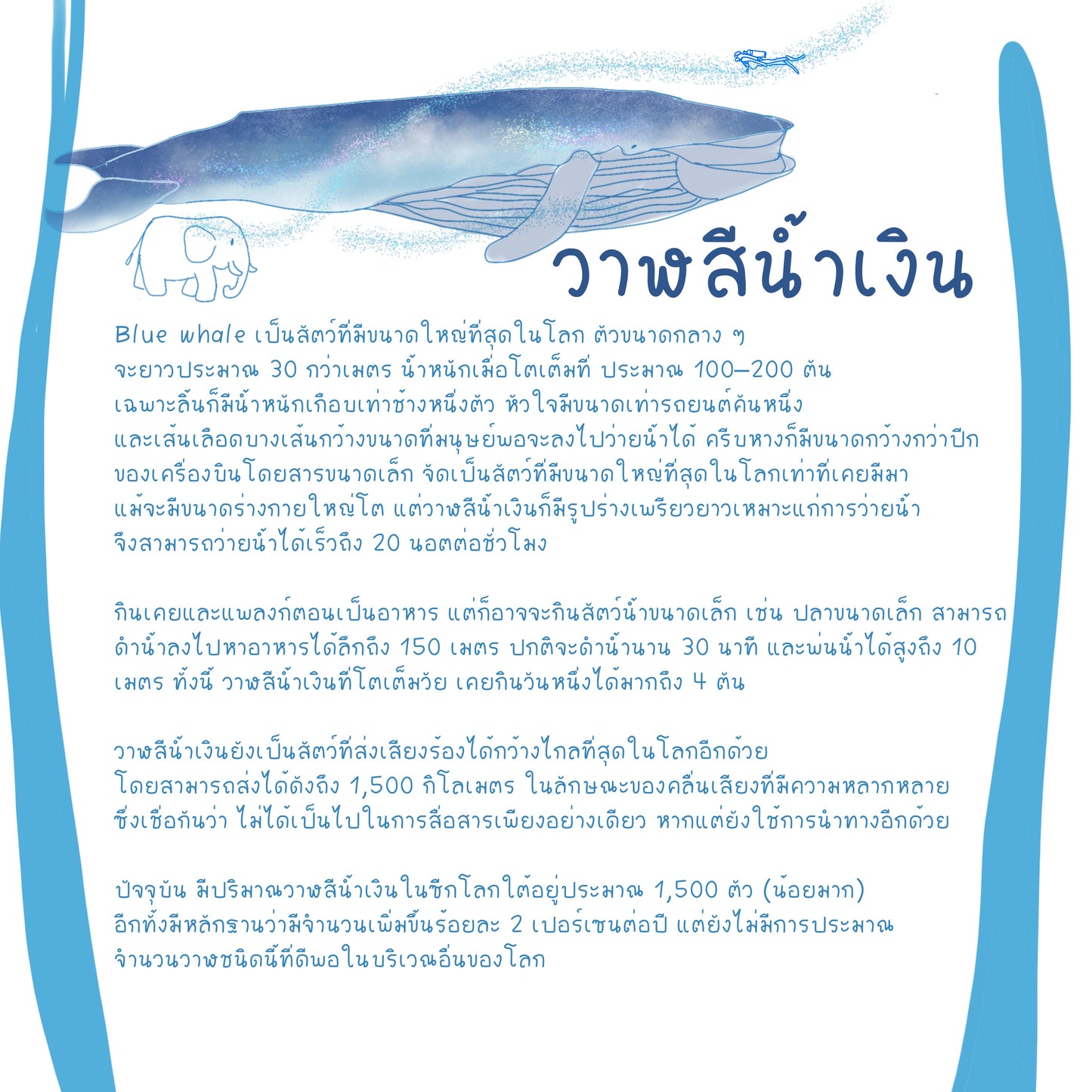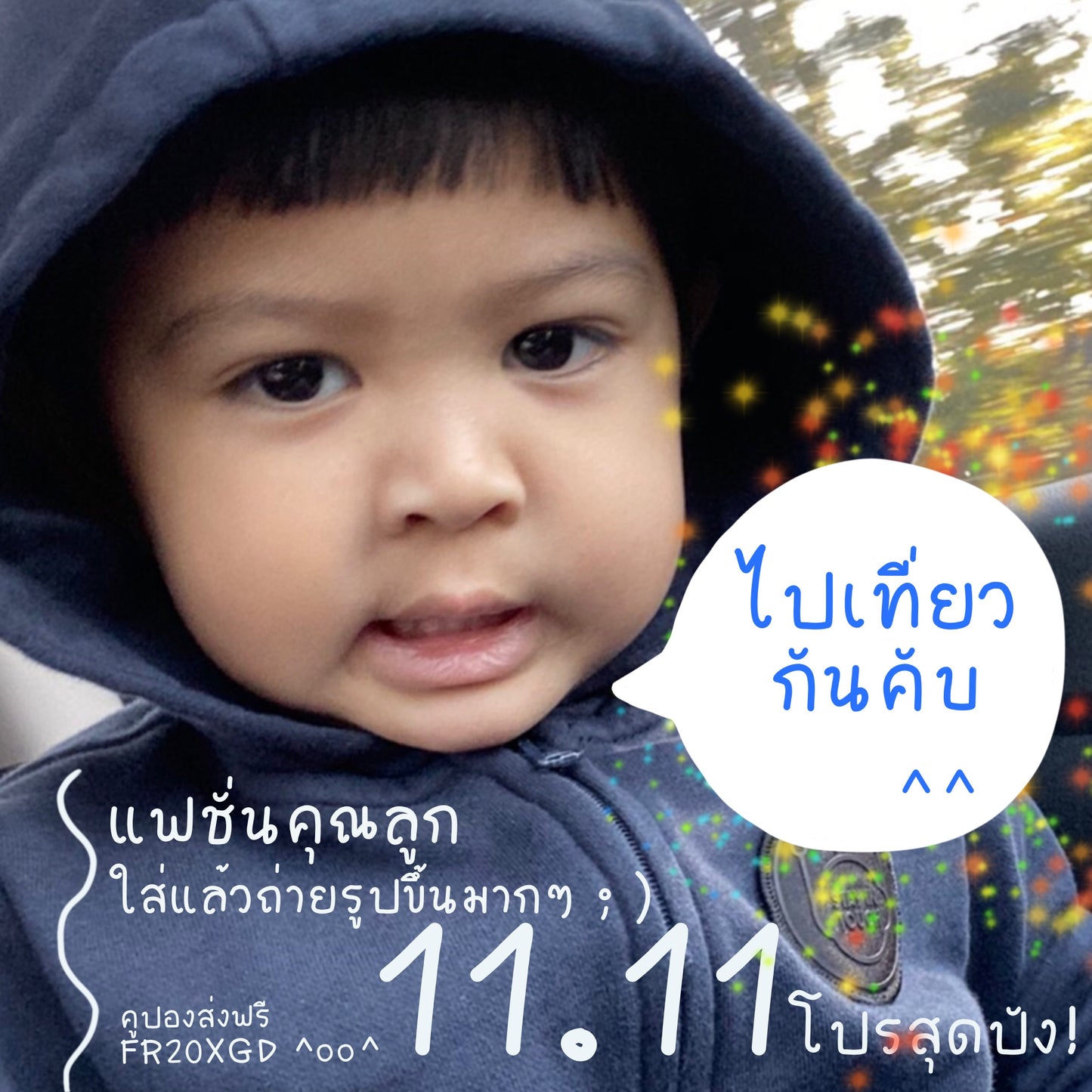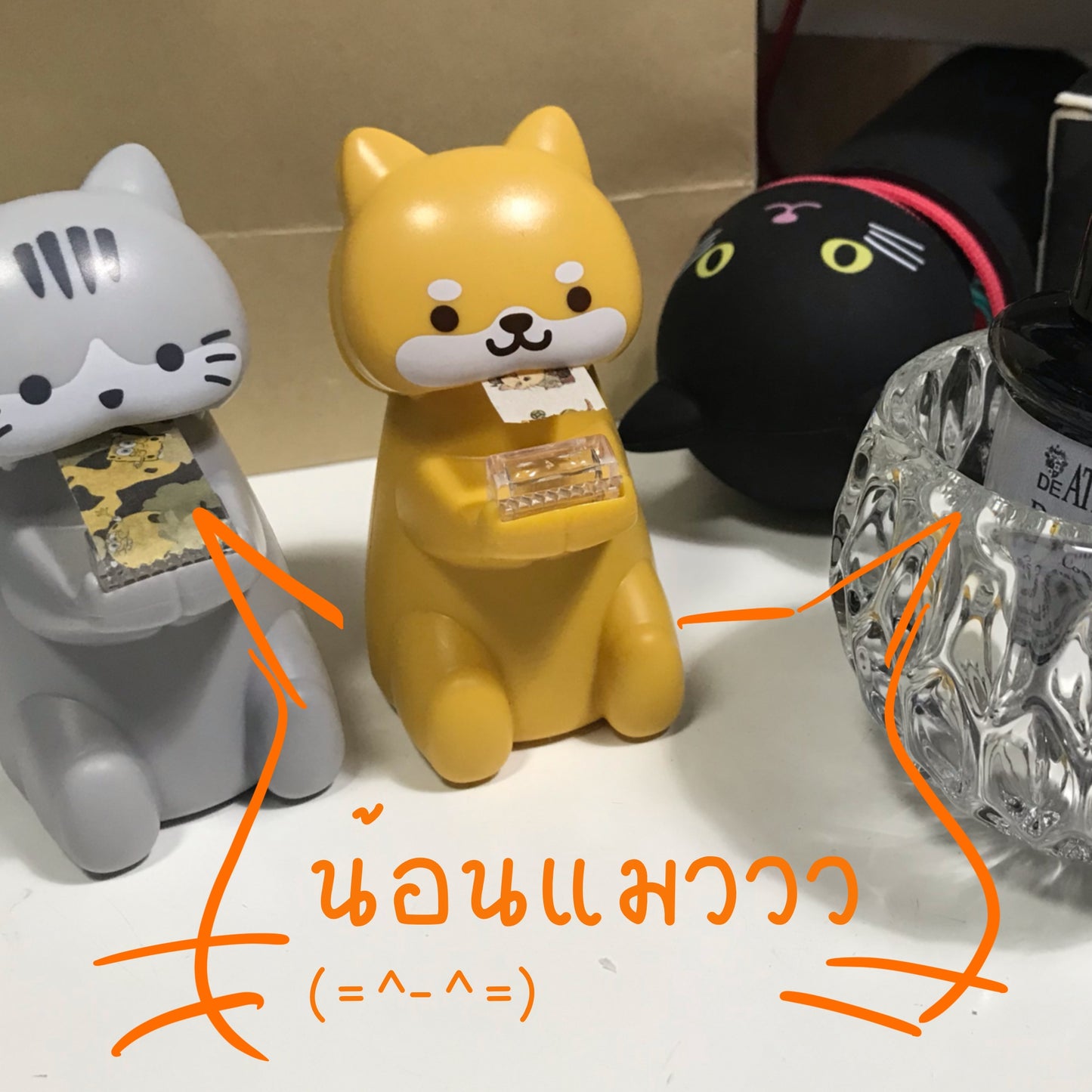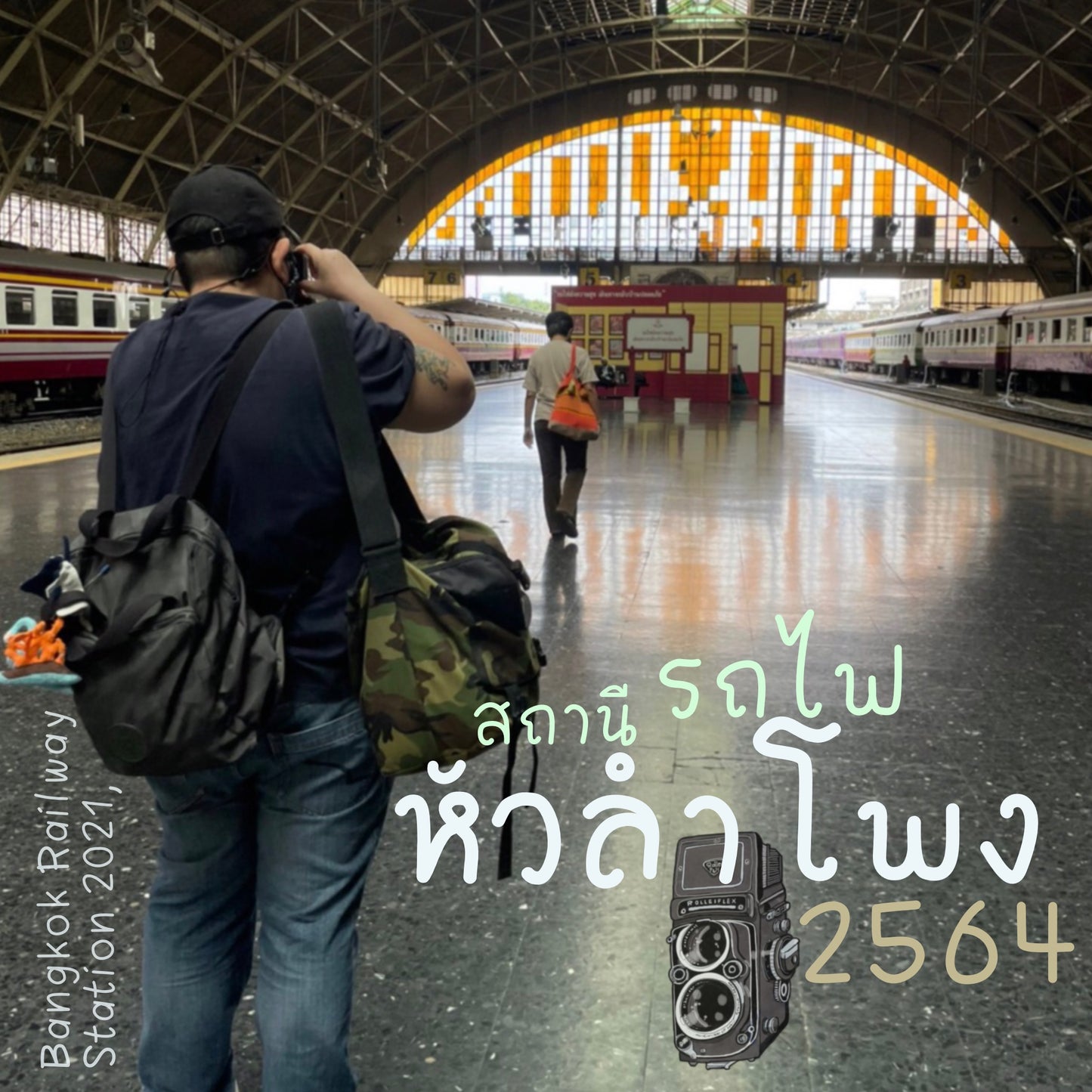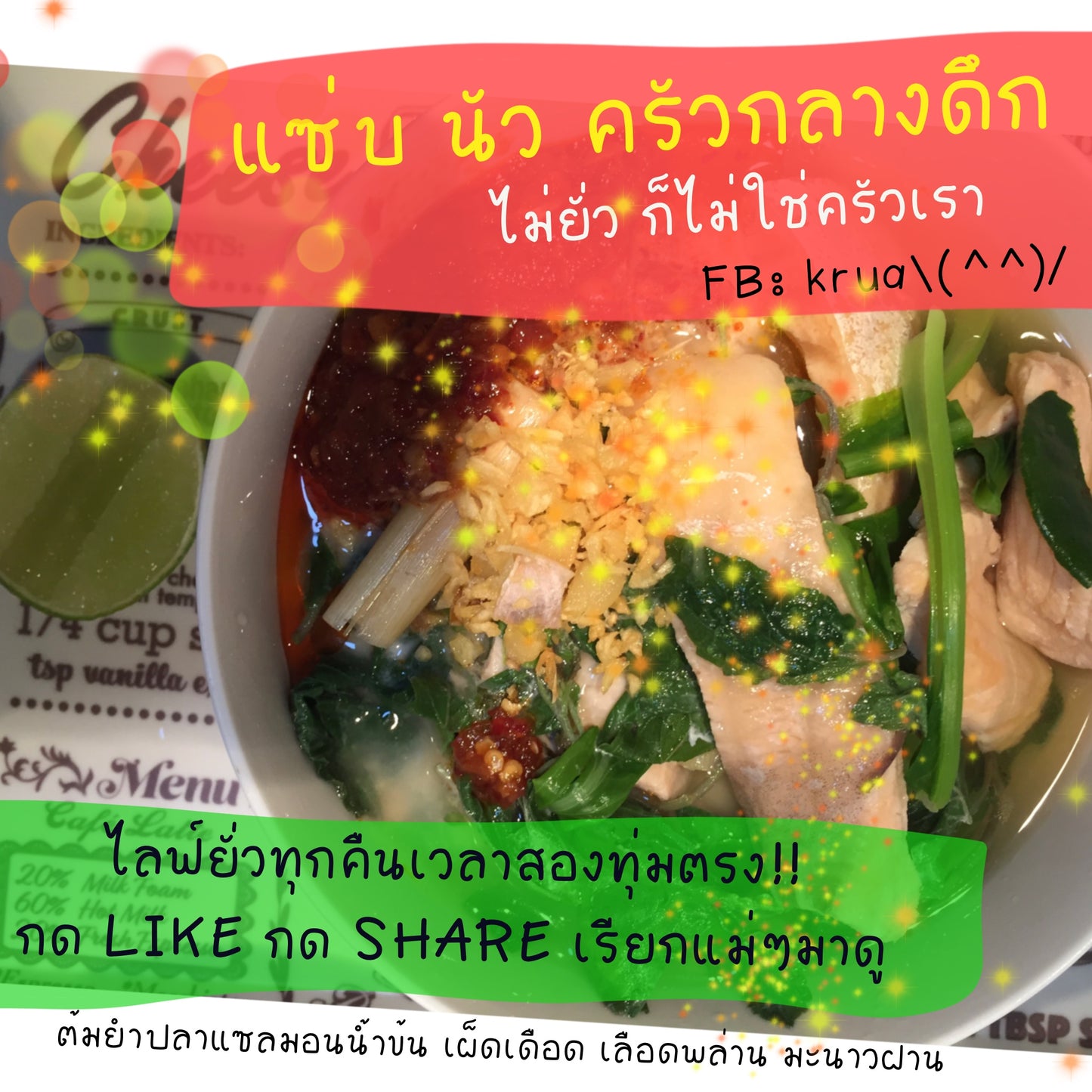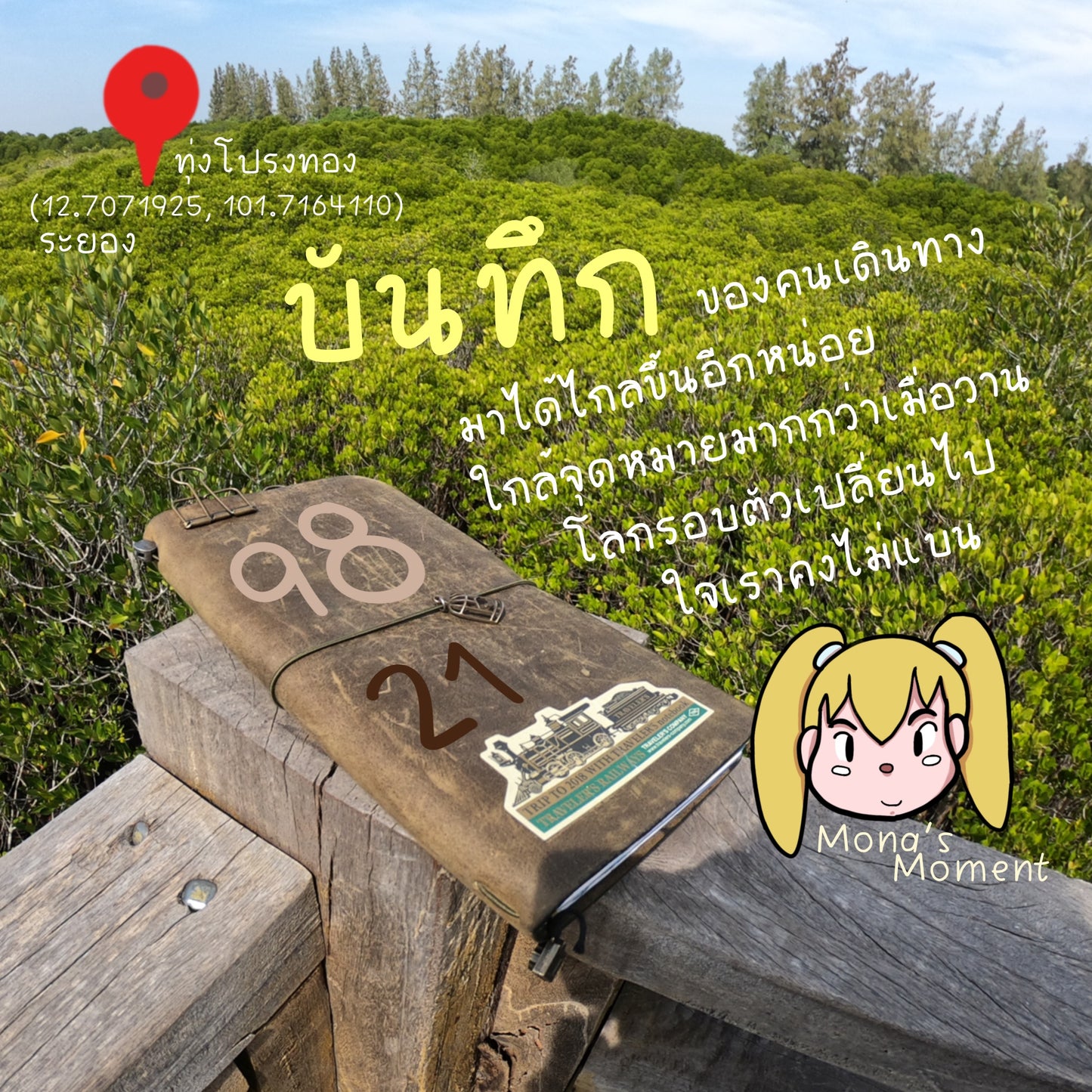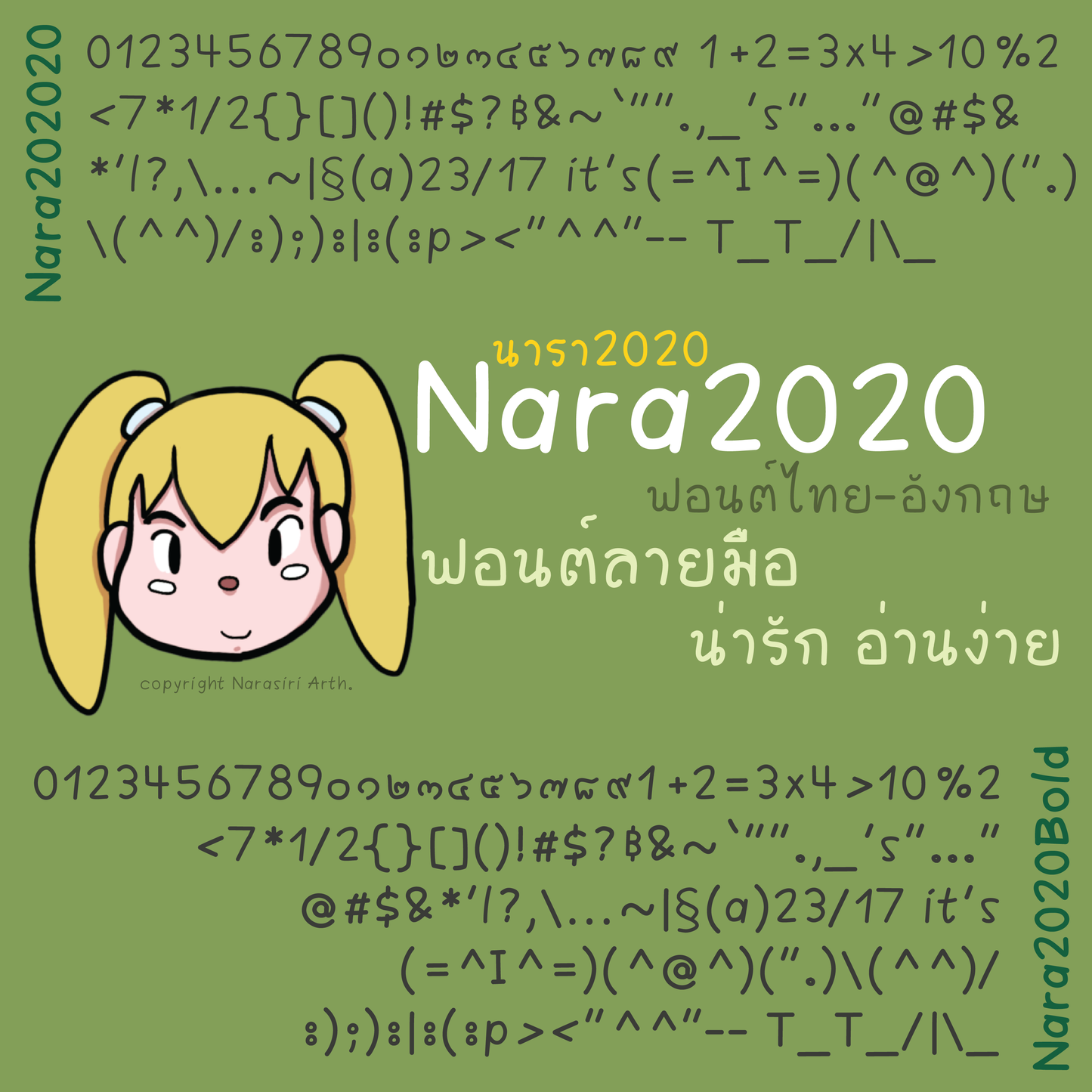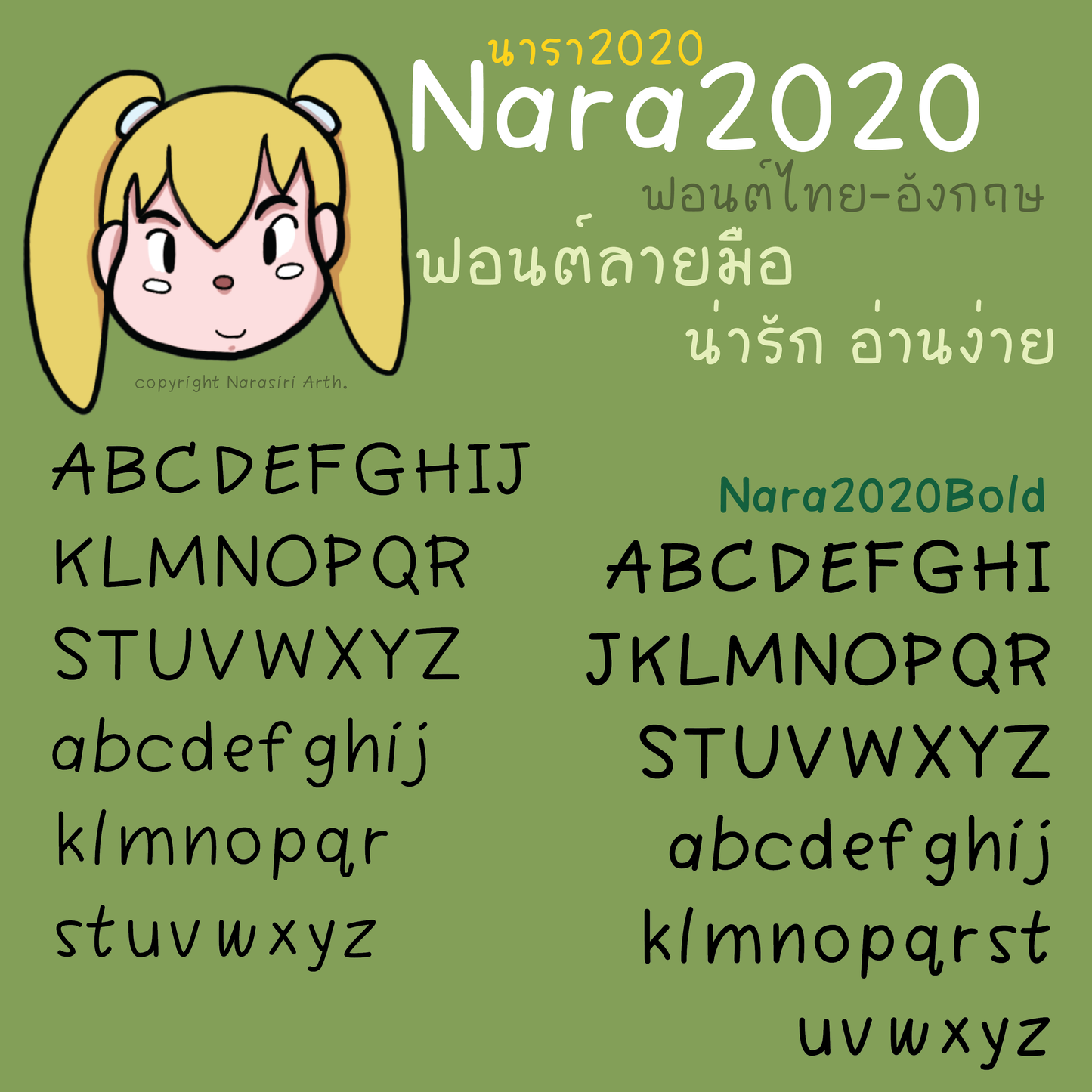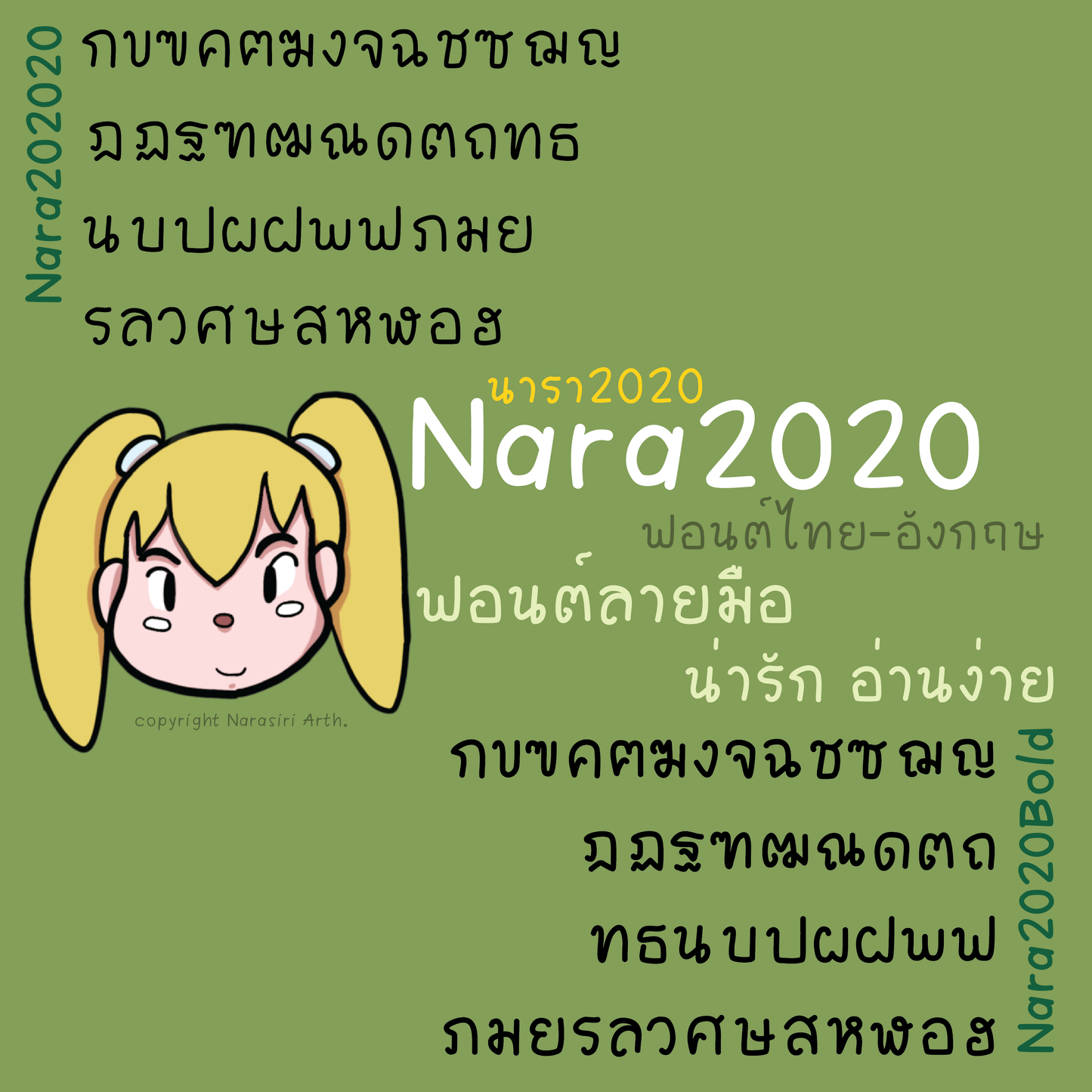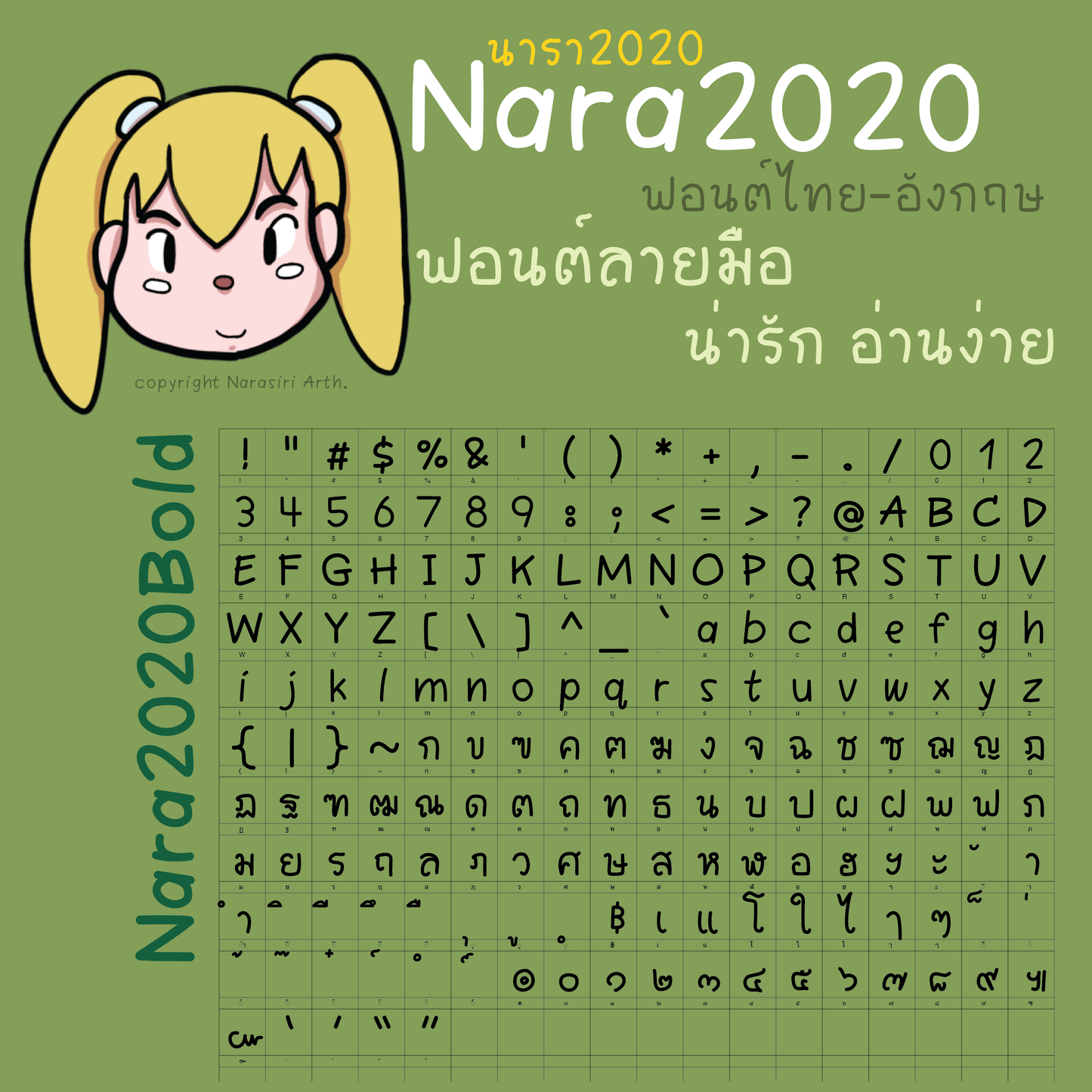
Nara2020 Font, Informal Handwriting Thai & English Font
Nara2020 ฟอนต์ลายมือ ภาษาไทย-อังกฤษ ลายมือเขียนแบบไม่เป็นทางการ ตัวเนี้ยบ เรียบร้อย อ่านง่าย สบายตา
แรงบันดาลใจในการออกแบบ
อยากได้ฟอนต์น่ารักๆแบบที่อ่านง่าย สบายตา เอาไว้ใช้เวลาเขียนสื่อสารกับลูกค้าใน Ad สินค้าที่เราขายออนไลน์ ฟอนต์น่ารักๆ ช่วยเสริมให้สินค้าดูน่ารักไปพร้อมๆกัน ^^
Nara2020 Font, Informal Handwriting Thai & English Font
Creator's Inspiration
Seeking some cute fonts to apply with Product Ad. Cute fonts help telling outstanding story for our products ^^